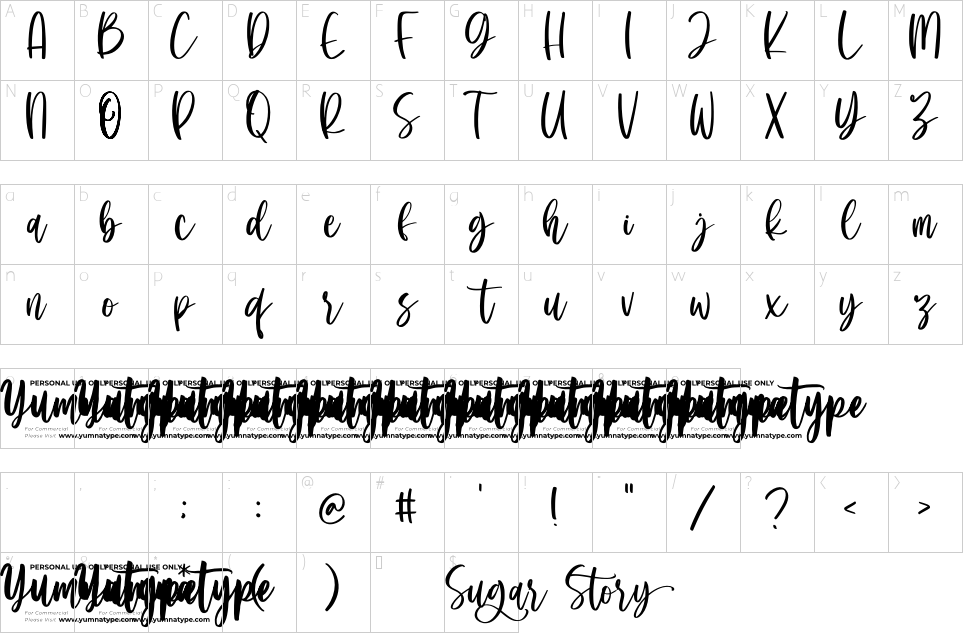
Descubra a sofistica e elegância do Sugar Story Font com uma experiência sem igual na categoria das fontes gratuitas. Desenvolvida por Yumna Type, essa font é perfeita para designers que buscam uma alternativa fresca aos estilos convencionais. Com 5.863 downloads já realizados, o Sugar Story proporciona um toque suave e moderno ao seu design. Seja para gráficos digitais ou criações de escritório, essa font é versátil e elegante, oferecendo uma ótima alternativa gratuita para quem valoriza qualidade sem comprometer no aspecto financeiro. Não perca tempo, teste e descubra por si mesmo as delícias deste Sugar Story Font incrível hoje!